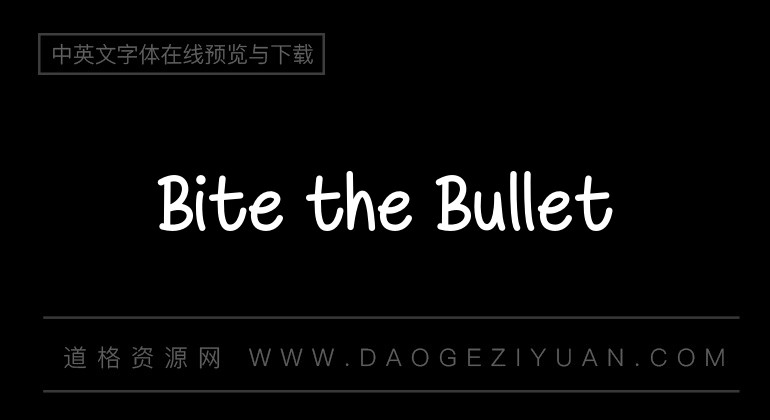
Bite the Bullet
Bite the Bullet 是一款英文字体,由英国设计师Nina Geometrieva设计,它是一款极具表现力,大胆而有趣的英文字体。它有着非常明显的视觉效果,可以用于创造出鲜明的文字。它的字符特征也非常丰富,可以满足各种不同的文字要求。它的字形结构也非常精致,可以让文字看起来更加精致,更具有表现力。
Bite the Bullet是一款非常不错的手写艺术字体,具有很好的视觉感,适合于文化类的宣传设计、商业类品牌的广告和产品包装设计以及个性化文字排版等较多场景。
Bite the Bullet字符映射图